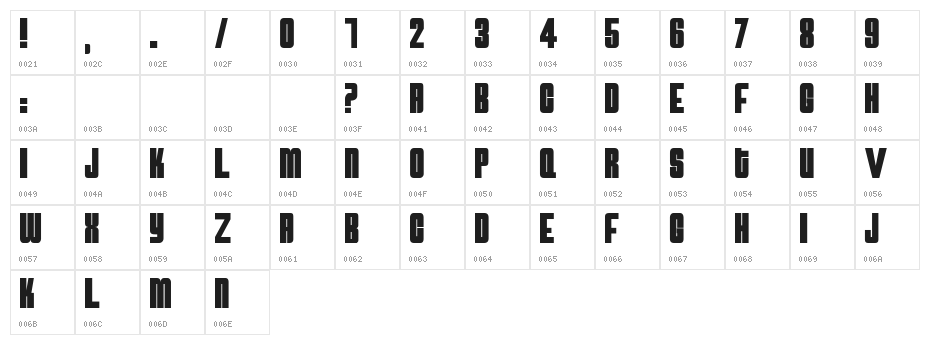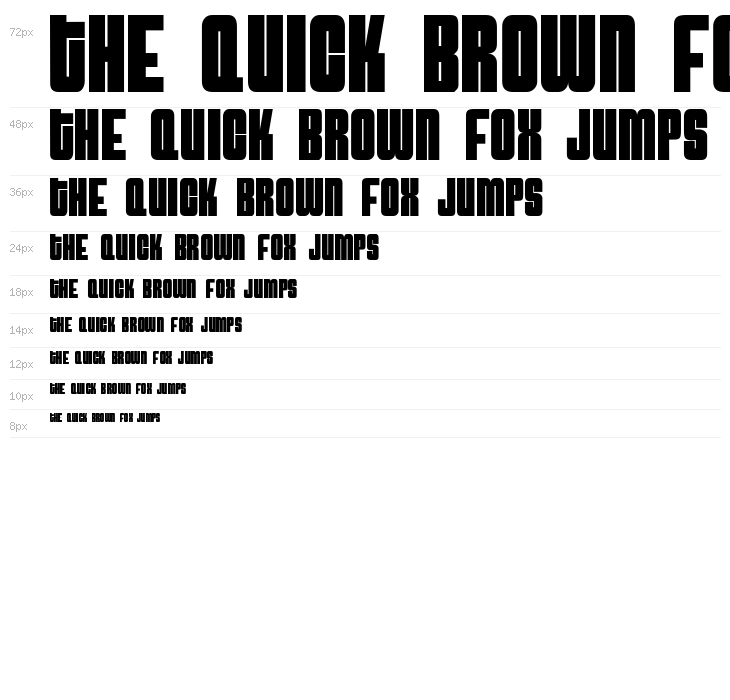
AtomicBomb Font
| उपयोग का मामला | Headlines, Logos |
| सुझाए गए प्रोजेक्ट | Ideal for posters, logos, and headlines where a strong, impactful presence is needed. |